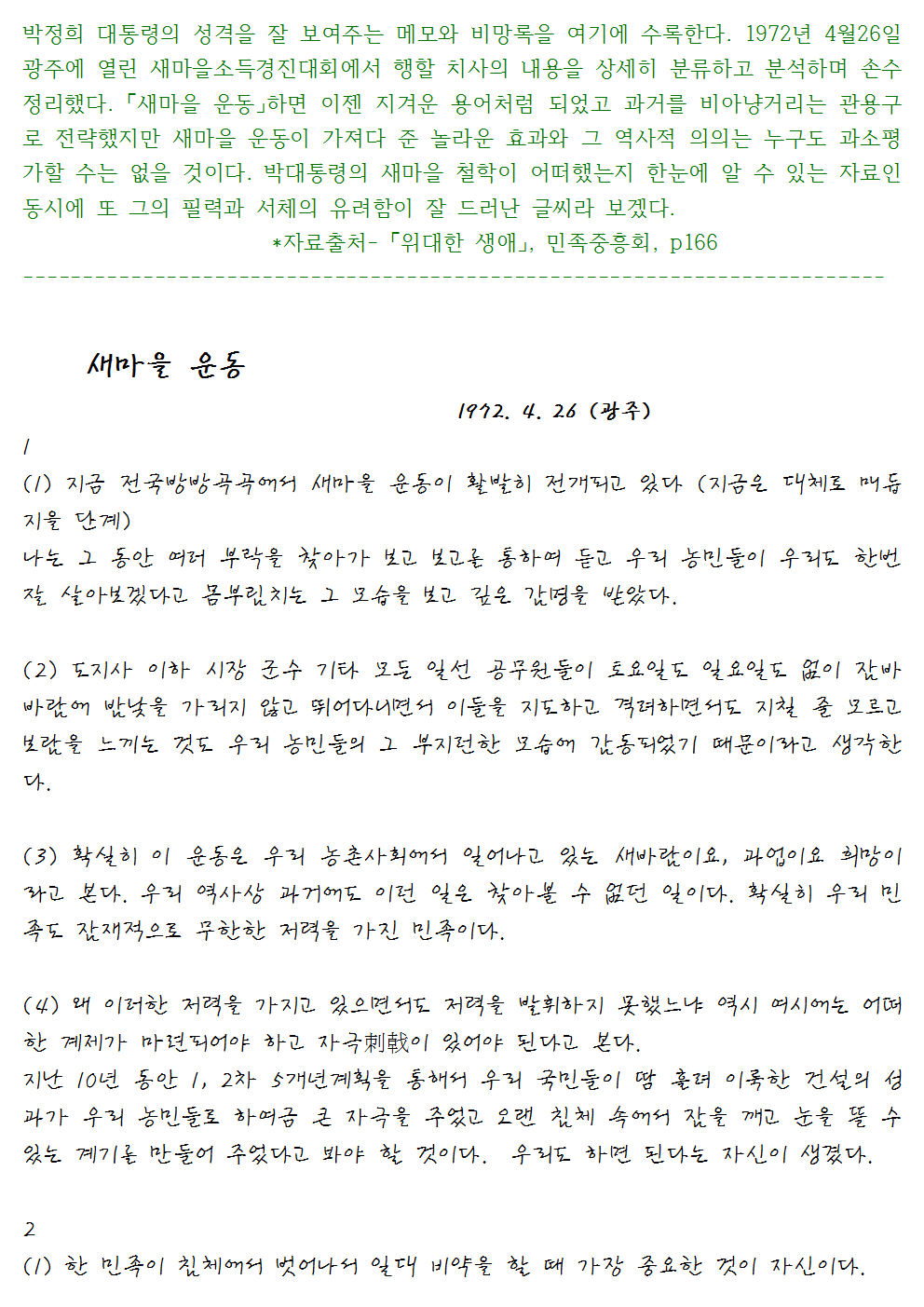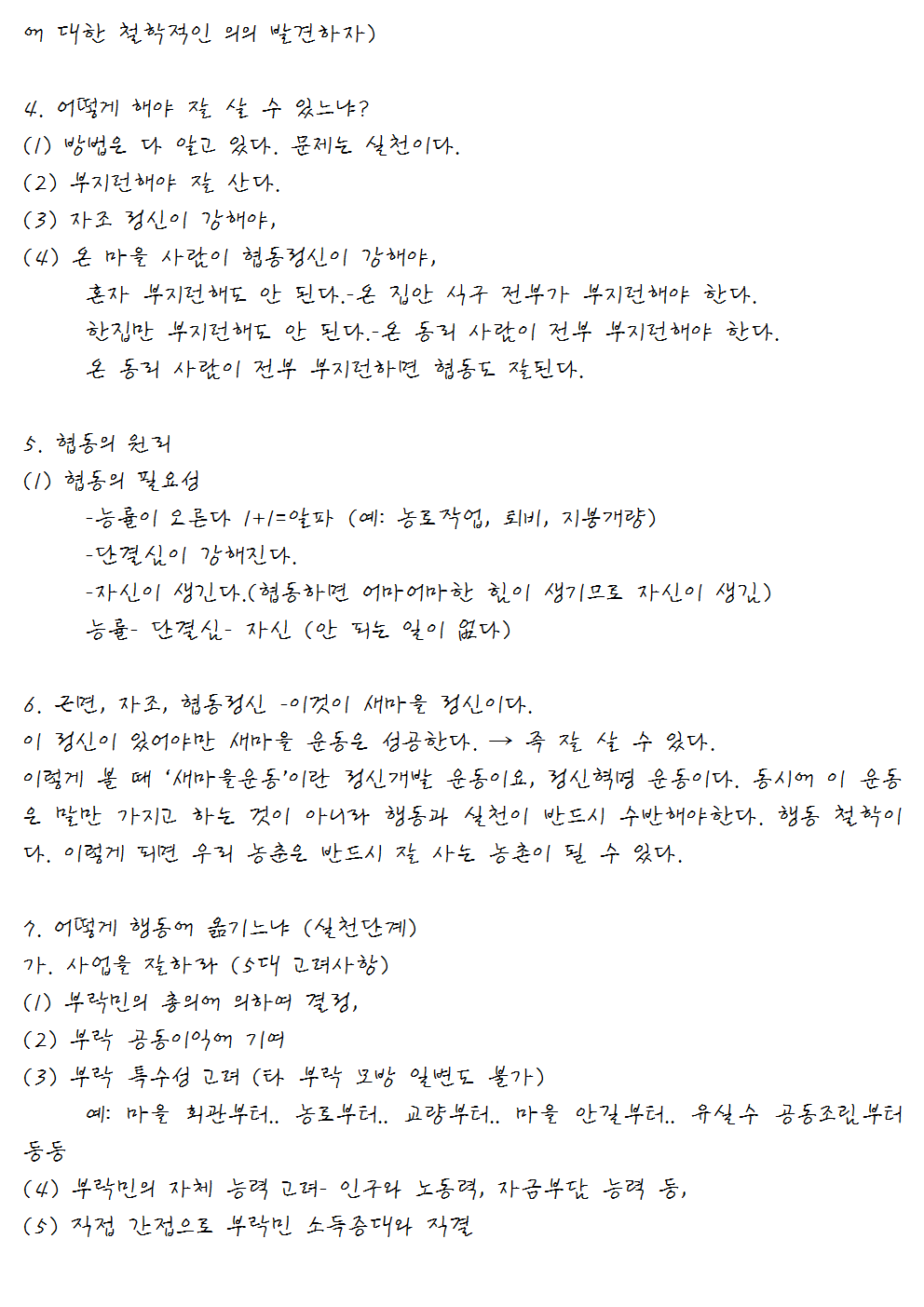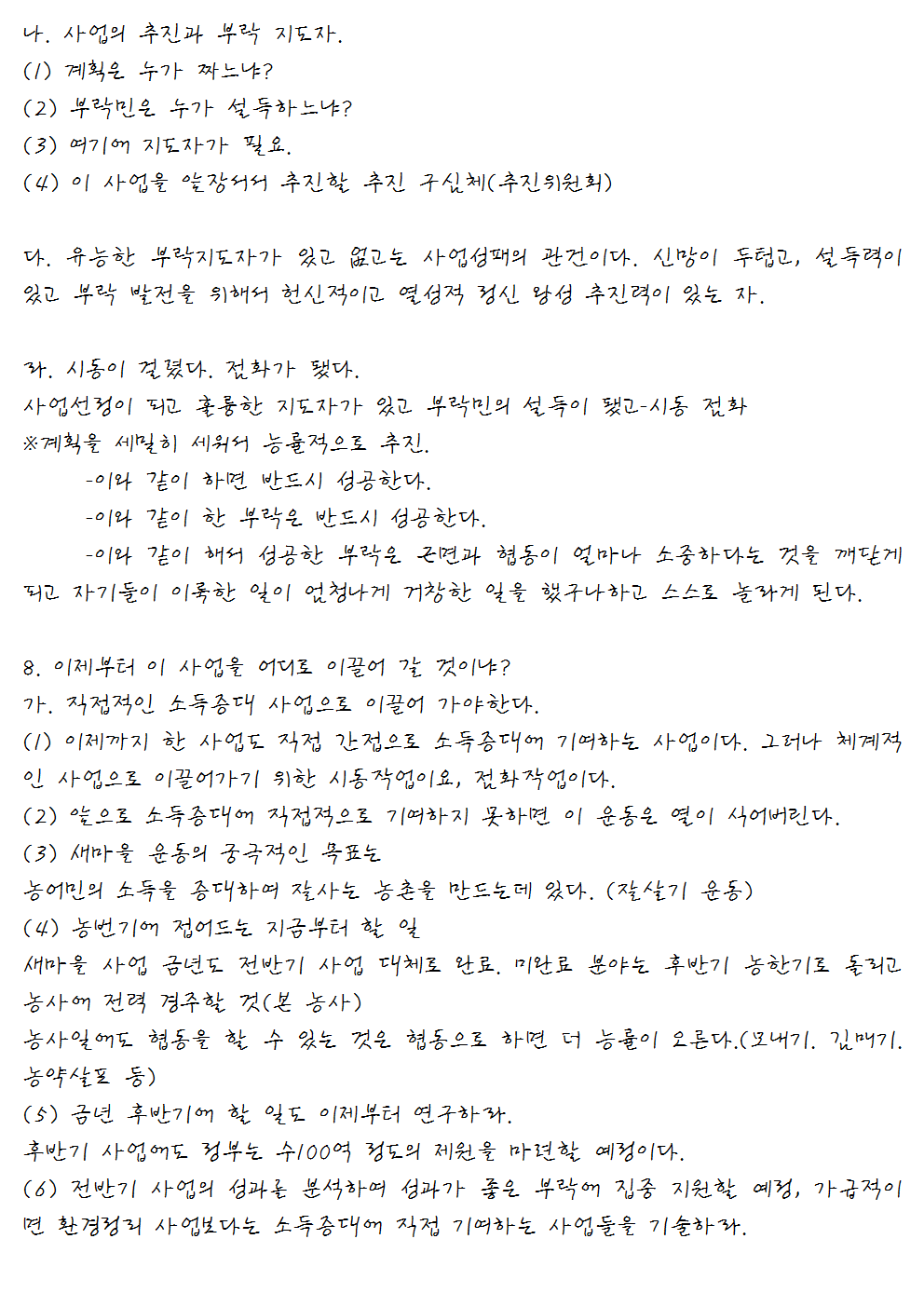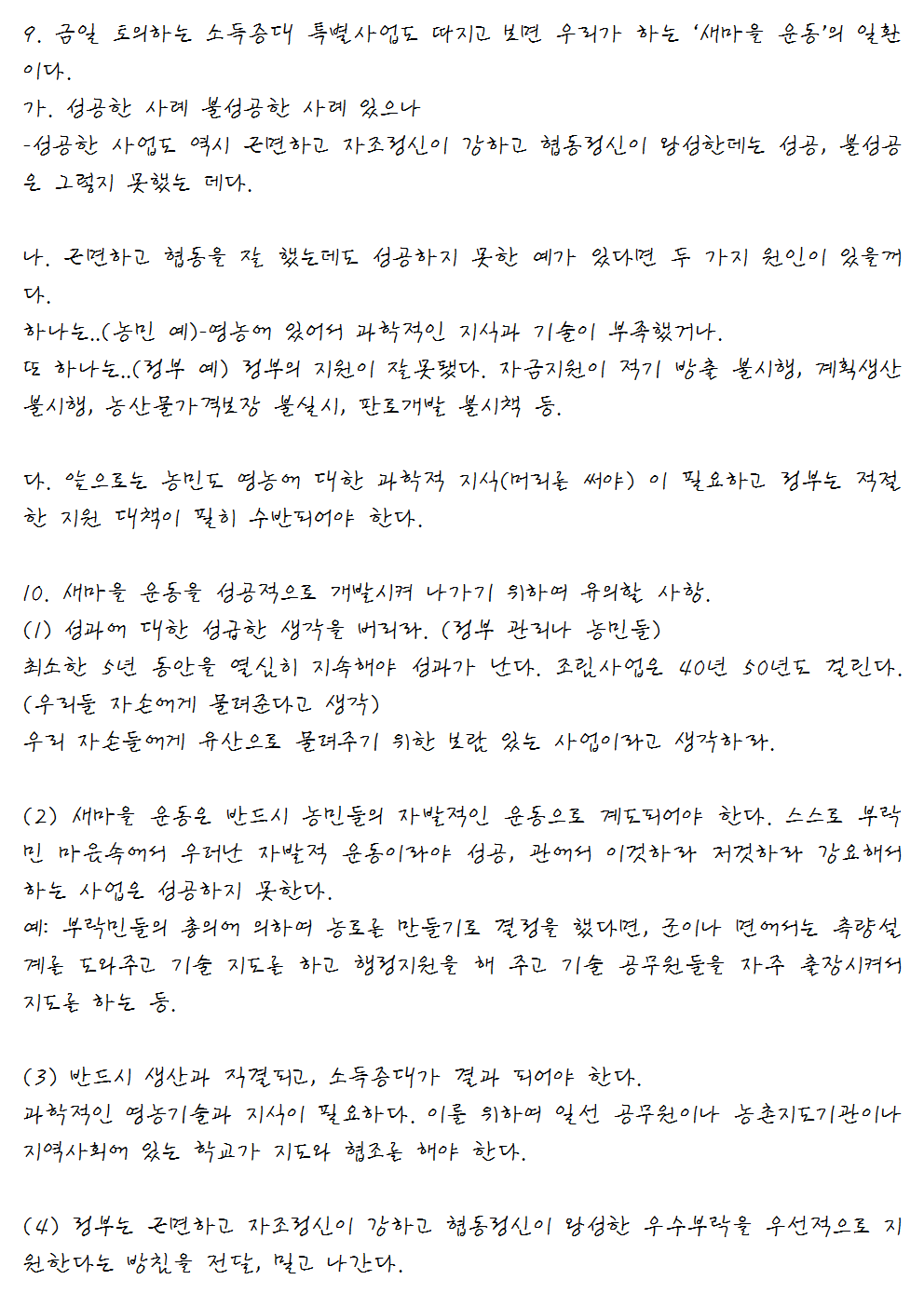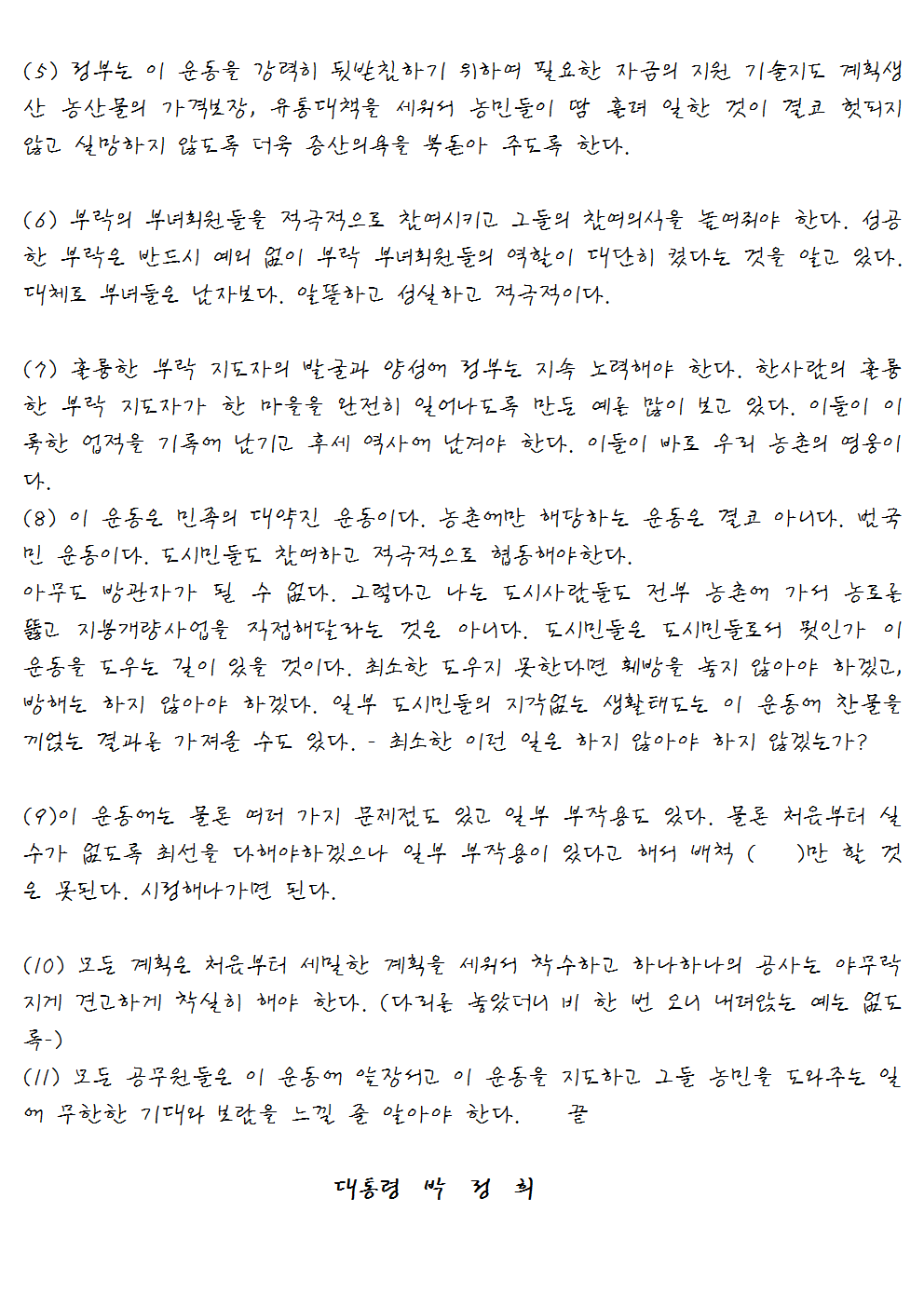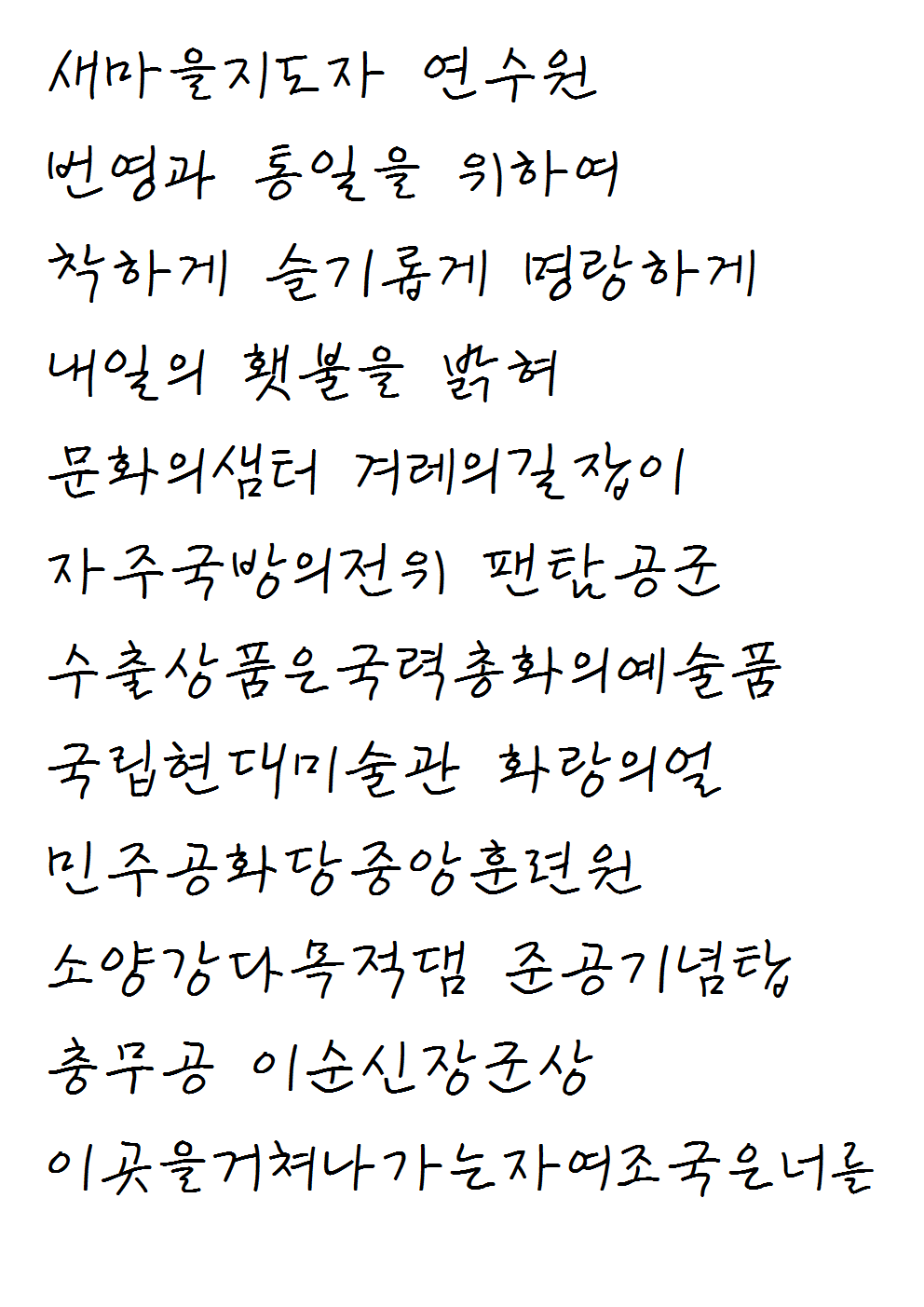
[tip]박정희새마을체_P : 영문명(KR_ParkCHungHee_P) : 동영상<새마을 노래> 자막 글꼴[/tip]
이 글꼴은 박정희대통령의 펜글씨를 글꼴폰트로 제작한 것인데 그가 남긴 연설문 초안, 메모지 기록, 서간문, 자작 노래가사 등에서 자료를 참고하여 오랜 시간을 거쳐 완성된 필기체 글꼴입니다.
펜글씨 특징을 보면, 초기에는 매우 정교하고 곧바른 글자를 써다가 후기에 들어서 글자가 가로로 누웠다가 세로로 누웠다가 제대로 정렬되지 못한 듯 보입니다. 그러나 그러한 필체가 오히려 유려함을 돋보입니다. 글씨는 마치 공간을 날아다니는 듯 유연하고 한자와 혼용했을 때는 멋진 조화를 이루고 한껏 멋을 풍기는 글씨입니다. 펜글씨 속에는 군인다운 기질보다는 집념에 찬 지도자의 강한 의지와 집념이 묻어있는데 ‘광주 새마을경진대회 연설문’에 담긴 박대통령의 철학이 그것을 말해 줍니다.
이 글꼴은 개인적으로 가장 애착을 가지며 사용용도는 손글씨처럼 다양하게 응용될 것이며 조국근대화체와 더불어 모바일용 웹서체로 응용할 수 있을 것입니다.